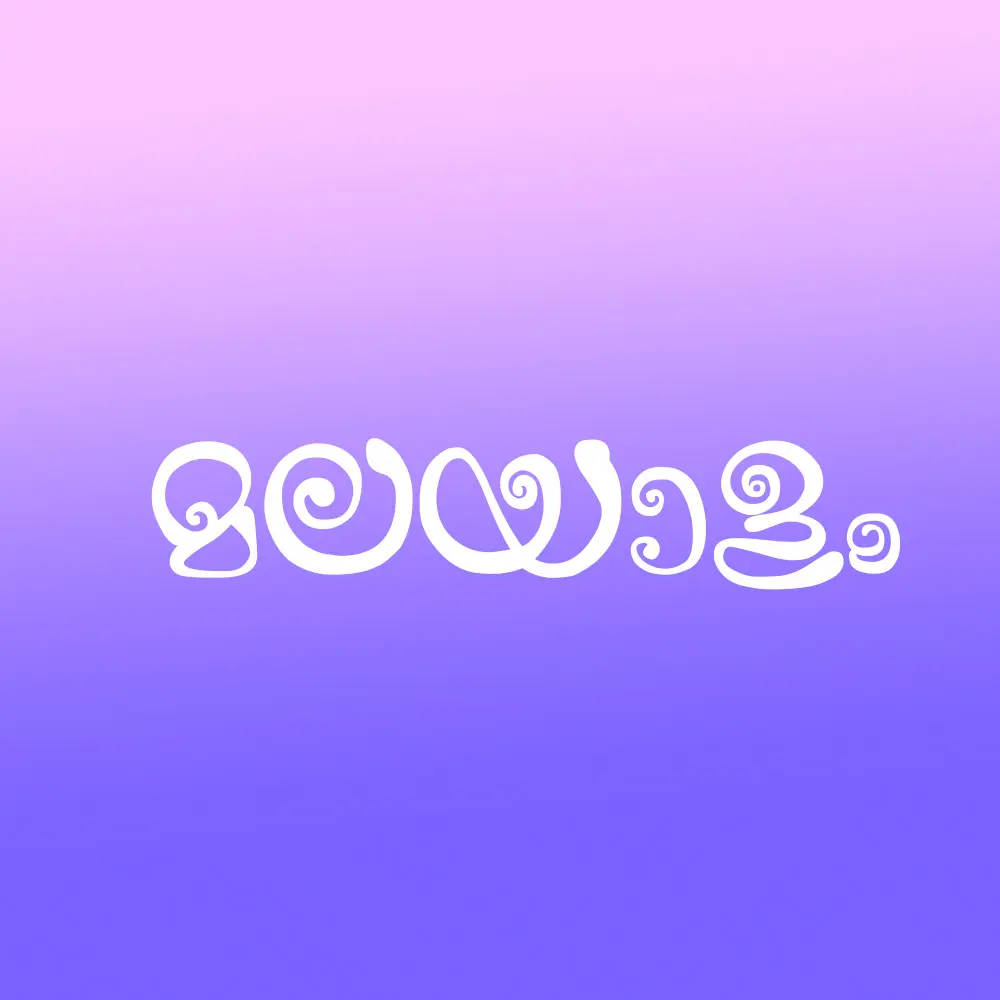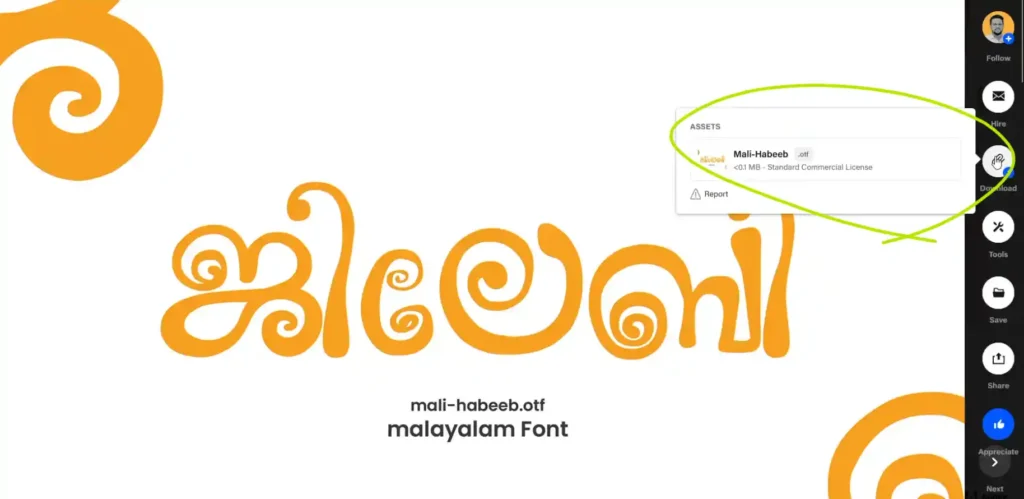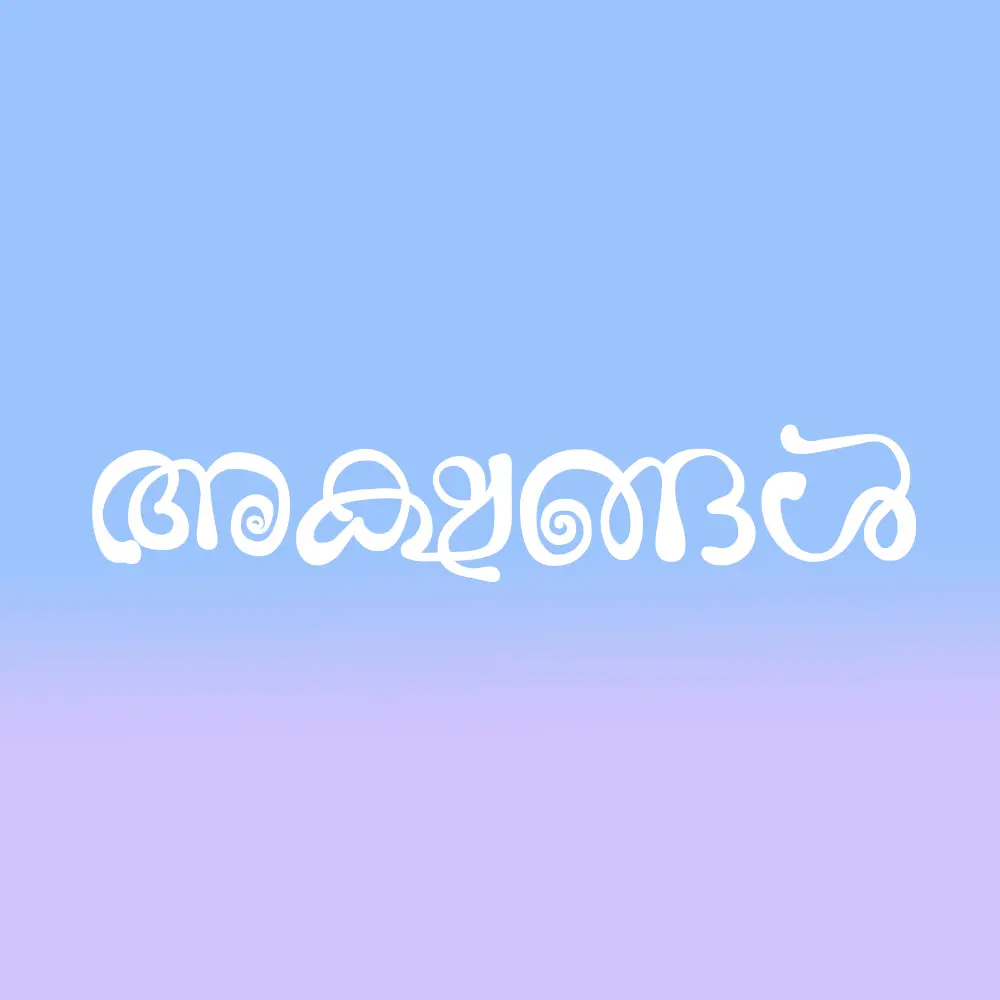
അതെ, നിങ്ങളുടെ ഡിസൈൻ പ്രോജക്റ്റുകൾക്ക് വേറിട്ട ഒരു മിഴിവ് നൽകാൻ പറ്റുന്ന ഒരു അത്ഭുതകരമായ ഫോണ്ട്—മാലി ഹബീബ്, അല്ലെങ്കിൽ ജിലേബി ഫോണ്ട് (Jelebi font) ഈ ഫോണ്ട് FML ഫോർമാറ്റിൽ ലഭ്യമാണ്, അതായത് സൗജന്യമായും പ്രവർത്തനക്ഷമമായും ഉപയോഗിക്കാനാവുന്ന ഒരു മലയാളം ഫോണ്ട്.
ഗ്രാഫിക് ഡിസൈനർ ഹബീബ് റഹ്മാൻ ഈ മനോഹരമായ ഫോണ്റ്റിന്റെ സൃഷ്ടാവാണ്. അതിന്റെ ചുരുണ്ടും വളഞ്ഞും പോയുള്ള സവിശേഷതകൾ, മലയാളത്തിന്റെ നന്മയും സവിശേഷതയും ഒരു പുതിയ മികവിൽ പുനർനിർവ്വചിക്കുന്നു. നിങ്ങളുടേതായ ബ്രാൻഡിംഗ്, പോസ്റ്റർ, വെബ് ഡിസൈൻ, അല്ലെങ്കിൽ മറ്റ് ക്രിയേറ്റീവ് പ്രോജക്റ്റുകളിൽ ഈ ഫോണ്ട് ഉപയോക്താക്കളുടെ ശ്രദ്ധ പിടിച്ചുപറ്റാൻ കഴിയും.
ജിലേബി ഫോണിന്റെ പ്രത്യേകതകളിൽ എന്താണ് പ്രധാനമായുള്ളതെന്ന് ചിന്തിക്കേണ്ടതില്ല—ഇത് വെറും ഒരുപാട് ആവേശകരവും സൗന്ദര്യപൂർണ്ണവുമായ ലേഖനം നൽകും. ഇത്തരത്തിൽ ഫ്രീ ഫോണ്ടുകൾ ഉപയോഗിച്ച് നിങ്ങളുടെ ഡിസൈൻകൾക്ക് പുതിയ ആത്മാവ് നൽകാൻ ഇപ്പോൾ ശ്രമിച്ചു നോക്കൂ!
Mali-Habeeb (Jelebi font) is a Malayalam font crafted specifically for impactful titles.